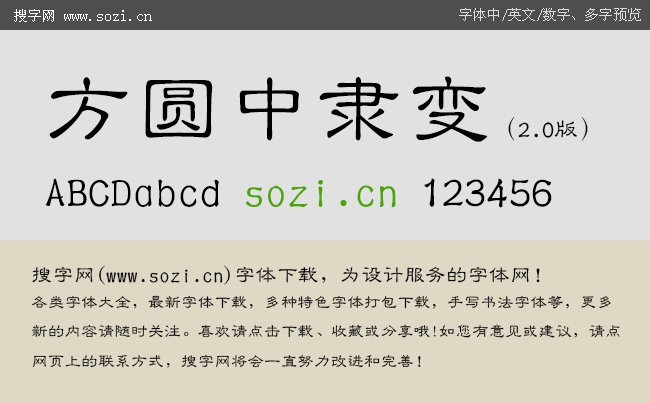
方圓中隸變
搜字網(wǎng)提供一款方圓中隸變中文字體下載,隸變體是漢字由篆書(shū)演變?yōu)殡`書(shū)的過(guò)程形成的字體。字型變圓形為方形,線條變弧線為直線,筆畫(huà)變繁雜為簡(jiǎn)省,徹底筆畫(huà)化。隸變是古今漢字的分水嶺。適用于畫(huà)冊(cè)設(shè)計(jì),海報(bào)設(shè)計(jì),圖書(shū)印刷等廣告設(shè)計(jì)場(chǎng)合使用。